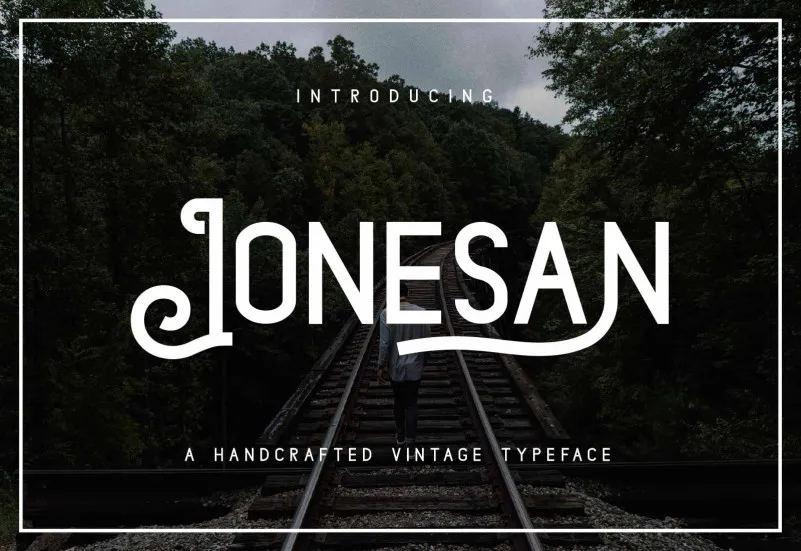
Jonesan Font – Fonte Grátis
Jonesan Font
A Jonesan Font é uma elegante sans serif que traz consigo uma sensação moderna e limpa, ideal para projetos profissionais. Esta tipografia foi lançada pela Galatamen e sua estrutura simples faz dela uma escolha perfeita para designers de todas as habilidades. Suas linhas retas e formas geométricas proporcionam um toque elegante em qualquer design, adequando-se facilmente a diversas tendências modernas. Com seu estilo limpo, a Jonesan Font é versátil o suficiente para transformar-se em uma das suas fontes preferidas, independente do tipo de projeto ou ocasião que você esteja lidando. Seja um design minimalista ou bem detalhado, essa fonte manterá sua identidade única e moderna sempre à mão.